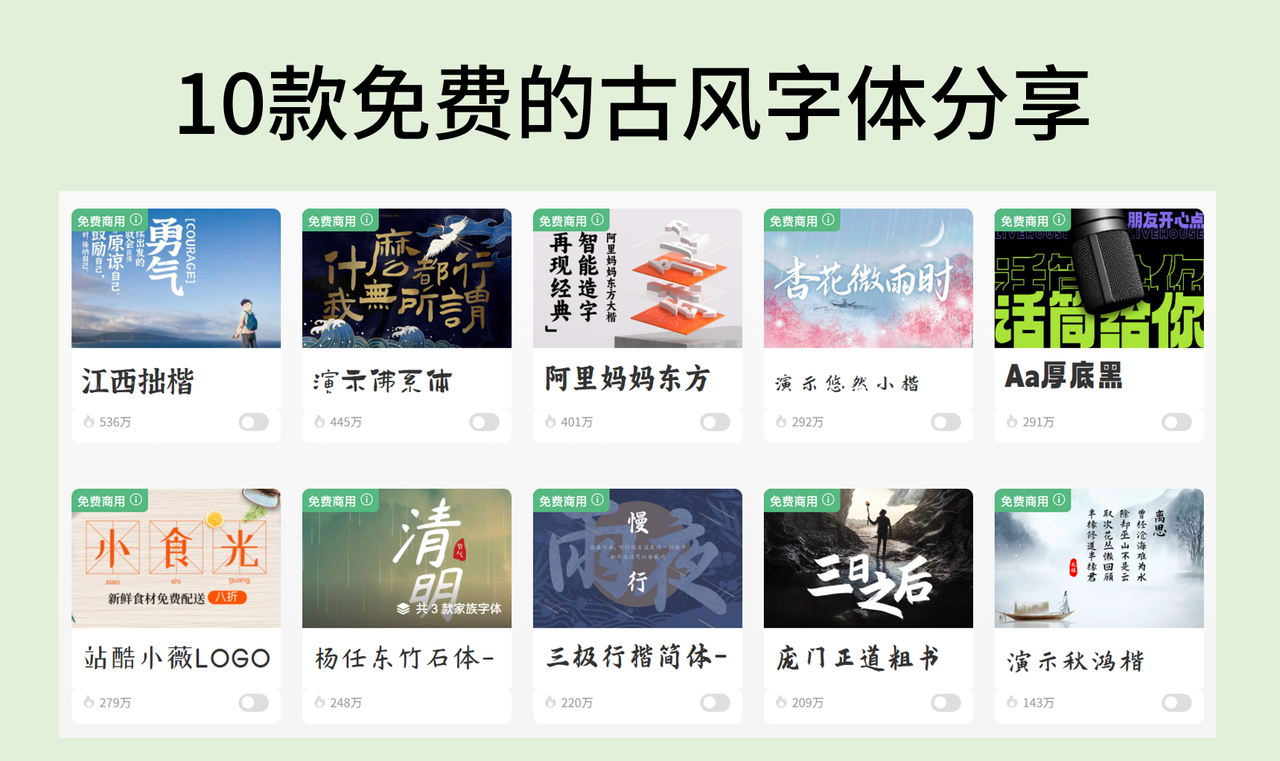
古风字体大全,10款免费商用的古风字体分享
你是否曾被一部古装剧的海报所吸引?是否曾为一款国风游戏的标题而惊艳?本文给大家介绍一下古风字体。它们不仅仅是文字的载体,更是是传统艺术与现代审美的完美结合。重点分享10款可以免费商用的古风字体。
什么样的字体是古风字体?
古风字体泛指那些在字形设计上融入了中国传统书法艺术、篆刻美学、以及古代文化元素的字体。它们通常带有浓郁的历史感、文化感和艺术感,能唤起人们对古代诗词歌赋、水墨丹青、金戈铁马的联想。
古风字体往往在笔画的起承转合间,流露出毛笔书写的韵味;在字形的结构布局上,体现出传统书法的章法意境,非常适合使用在一些文化艺术、武侠游戏、古装电影等场景。
古风字体在现代设计中的应用
- 影视与娱乐:
古装剧、武侠片、仙侠剧的片头、海报、宣传语,乃至游戏UI设计,都离不开古风字体的加持,它们能迅速营造出故事背景和氛围感。
- 图书出版与包装:
文学作品、历史读物、诗集、文化礼品、茶叶、酒水等产品的包装设计,常常运用古风字体来提升产品的文化品位和艺术价值。
- 网页与新媒体:
国风网站、文化类公众号、短视频标题等,通过古风字体能更好地吸引目标受众,传递内容主题,提升用户体验。
- 艺术展览与文创产品:
博物馆展览、文化节庆、文创周边产品,古风字体是表达主题、提升文化感知和深度比较好的选择。
10 款免费的古风字体分享
演示秋鸿楷
演示秋鸿楷是一款笔画流畅、结构端庄的楷书字体。它在传统楷书的基础上进行了现代化处理,笔锋圆润而不失骨力,字形规整大方,既有古朴韵味又兼具清晰的现代感。所以我把它作为第一个推荐的古风字体,非常设计书籍封面、文化宣传海报、教育课件、国学讲堂、茶艺空间、文创产品包装等场景。
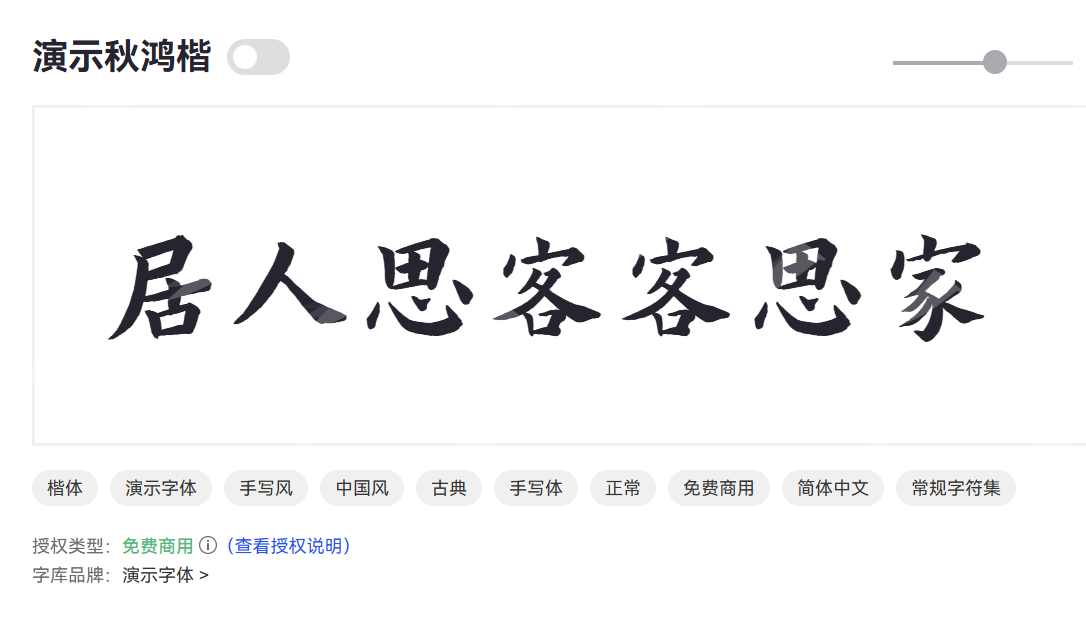
庞门正道粗书体
庞门正道粗书体是一款力量感十足的粗犷书法字体。其笔画粗壮有力,带有明显的书写痕迹和飞白效果,字形结构大胆奔放,充满视觉冲击力。
庞门正道粗书体适合表达磅礴气势、具有复古潮流,赋予品牌强烈的个性。比较适合品牌 LOGO、广告海报主标题、活动宣传物料、餐饮招牌、电影片头、游戏宣传等场景,我曾经在一个古装电视剧海报中就利用了这款字体。
三极行楷简体
三极行楷简体是一款融合了行书的流畅与楷书的端正的字体。它笔画连贯自然,字形稍带倾斜,既保留了行书的灵动飘逸,又兼顾了楷书的工整易读,整体风格优雅大方。
这款古风字体比较适合诗词排版、文化活动宣传、文创产品等场景。
杨任东竹石体
杨任东竹石体是一款充满东方禅意的艺术字体。它将竹的挺拔与石的坚韧融入笔画之中,线条或劲直或圆润,字形古朴自然,适合传达宁静、质朴、与自然和谐共生的品牌理念。所以它适合茶道品牌、素食餐厅、文旅宣传、艺术展览、国风等设计场景。
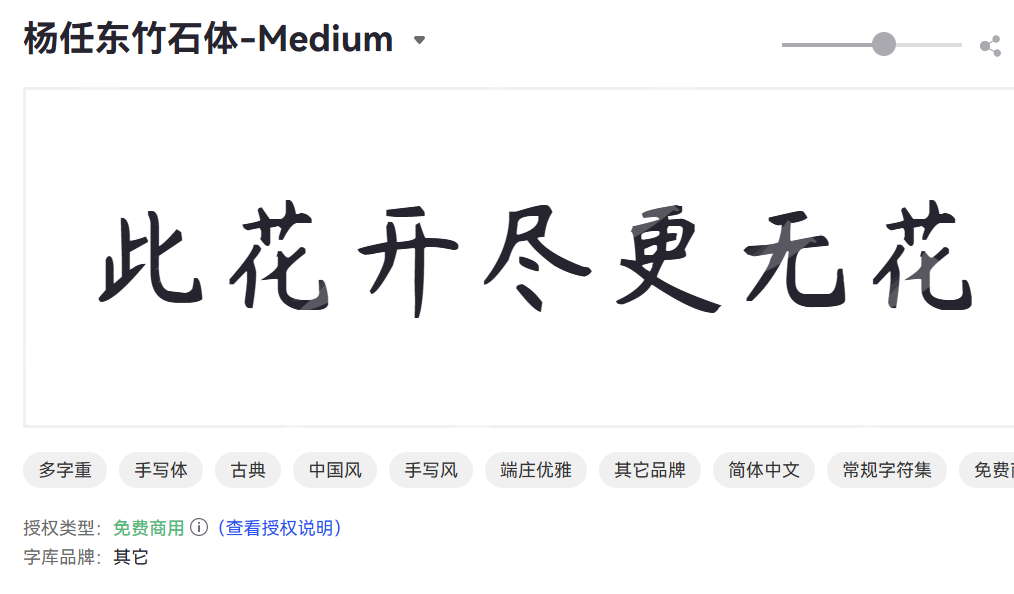
站酷小薇LOGO体
站酷小薇LOGO体是一款专为品牌标志设计而创作的个性化字体。它字形结构简洁而富有张力,笔画粗细对比强烈,部分笔画经过巧妙的几何化处理,时尚感与辨识度都非常的不错。
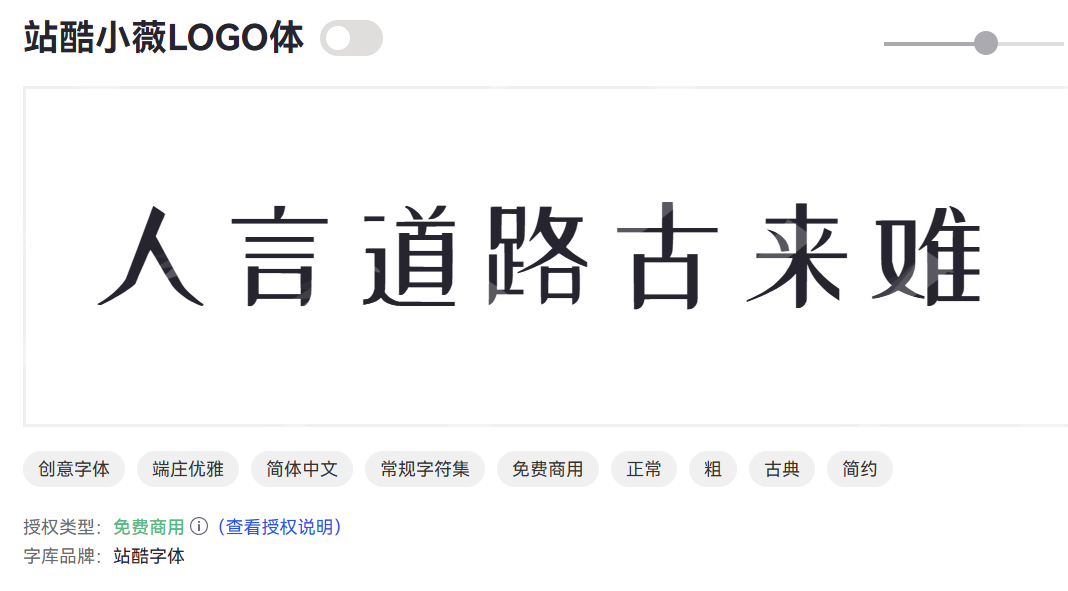
Aa厚底黑是一款极致粗壮的黑体字体,极粗的笔画在任何背景下都能清晰呈现,确保信息被快速捕捉。适用于科技、工业、运动等需要表现力量和现代感的领域。例如户外广告牌、大型海报标题、电商促销标语、科技产品发布等场景。
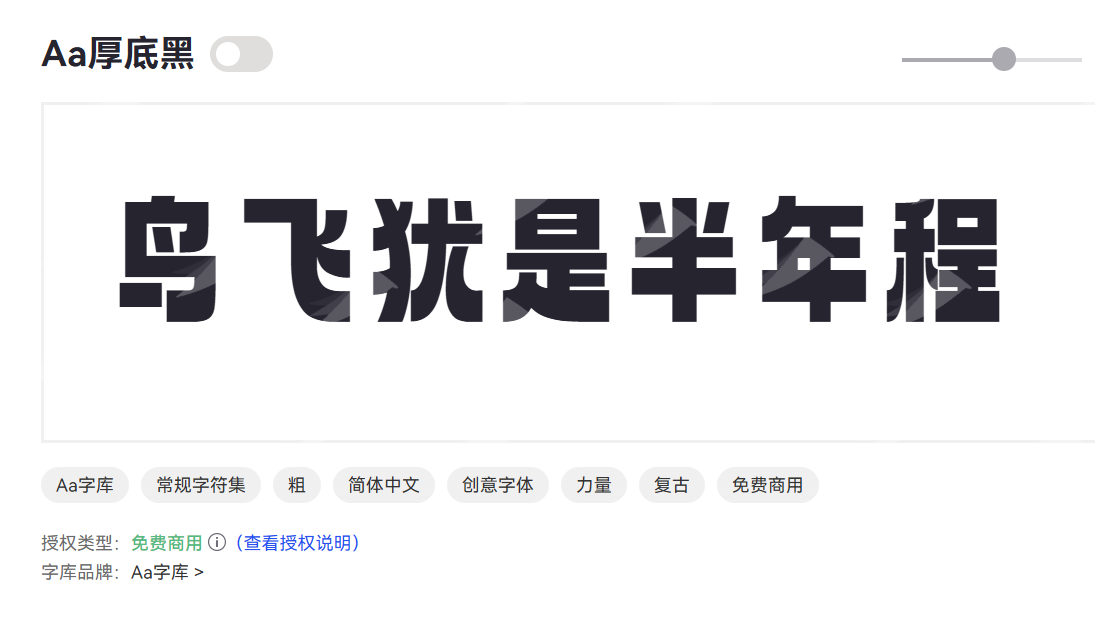
演示悠然小楷
演示悠然小楷是一款笔画纤细、字形清秀的小楷字体。整体呈现出一种宁静、悠远、温润的东方美感。适合表达柔和、细腻的情感,提升内容的文化品味和格调。
这款古风字体同样适合茶道文化、国风服装品牌、诗词歌赋排版、高端文创产品、艺术展览等场景。
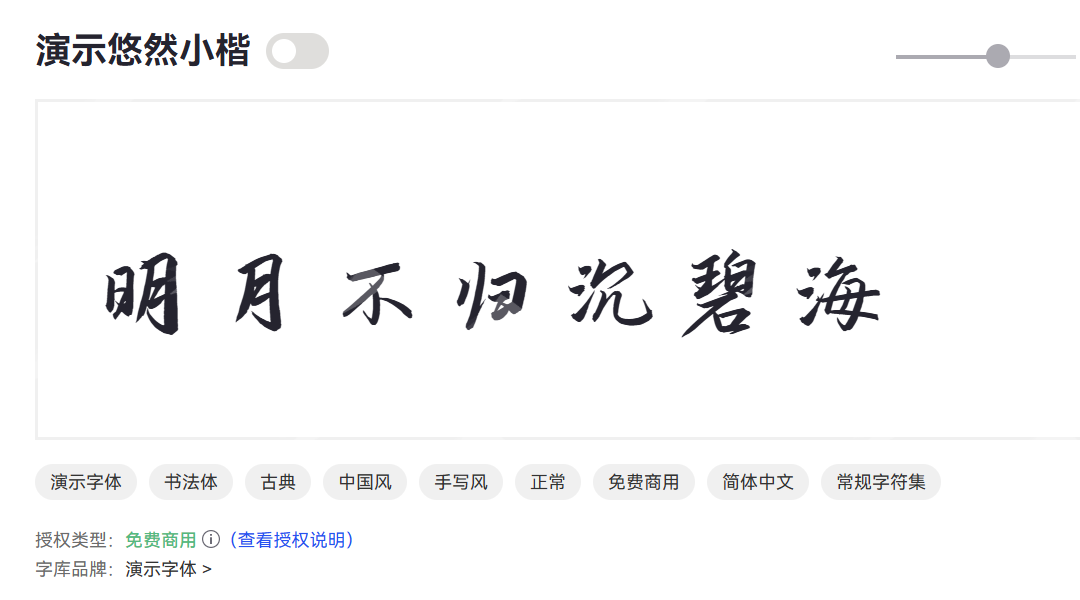
阿里妈妈东方大楷
阿里妈妈东方大楷是一款雄浑大气、气势磅礴的楷书字体。字形方正开阔,兼具古朴的东方韵味与现代设计的力量感。
阿里妈妈东方大楷蕴含深厚的传统文化气息,适用于需要突出民族特色和文化传承的场景。
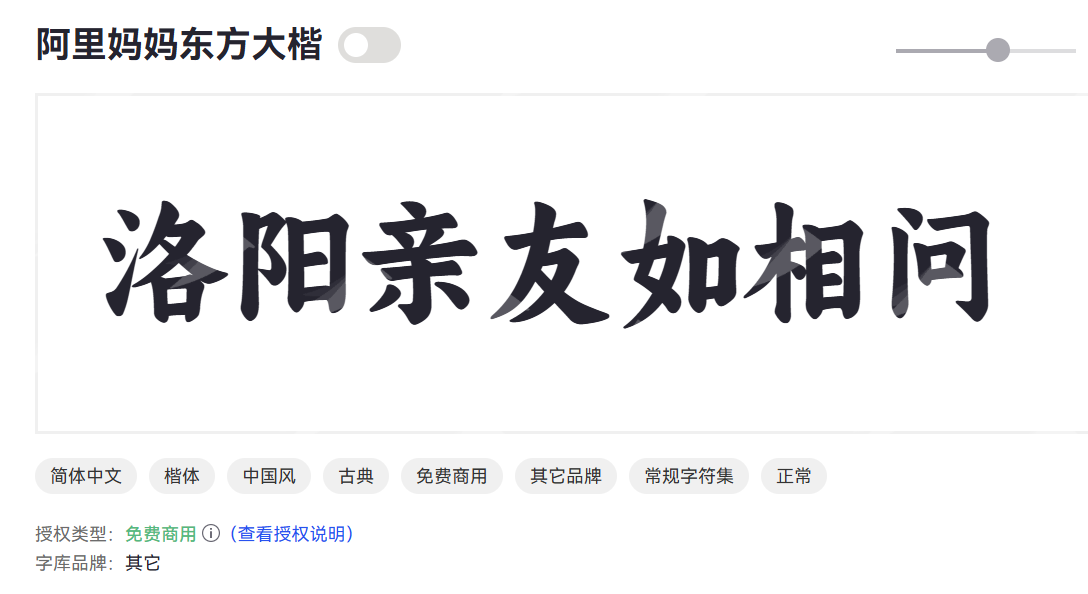
演示佛系体
演示佛系体是一款极简、宁静且带有手写笔触的创意字体。它的笔画简洁流畅,字形舒展放松,刻意减少了笔锋的棱角,整体呈现出一种平和、随性的“佛系”气质。所以这款古风字体适合一些慢生活的场景,比如瑜伽冥想馆、咖啡馆招牌、生活美学博客、治愈系产品等等。
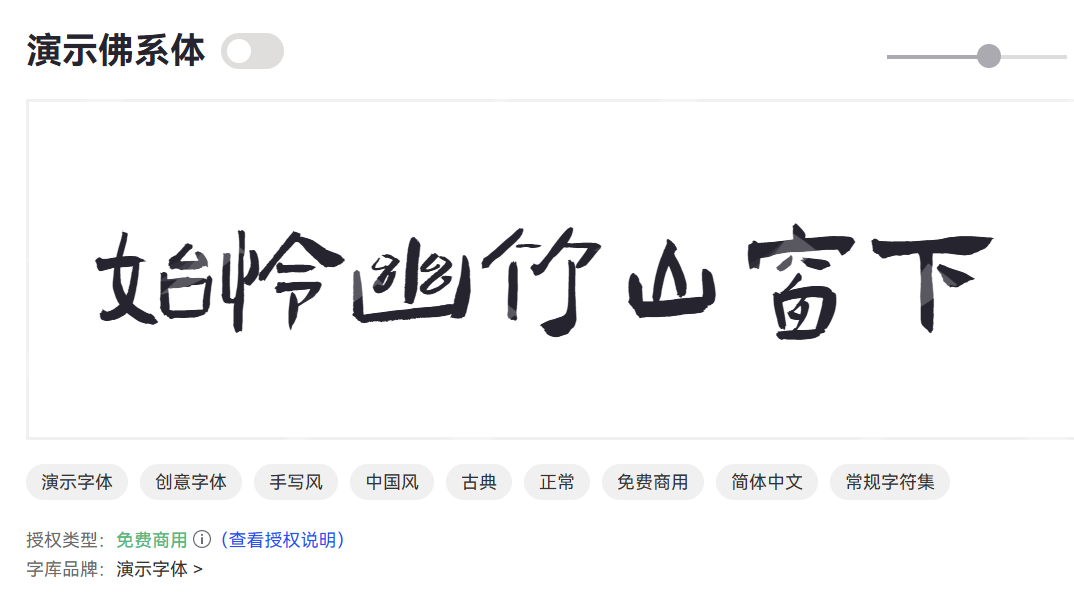
江西拙楷
江西拙楷是一款朴实无华、带有天然拙趣的楷书字体。它笔画自然随性,字形结构不拘一格,仿佛出自民间艺人之手,散发出一种返璞归真的质朴魅力。适合表现地方文化、传统工艺或农产品等原生态主题。